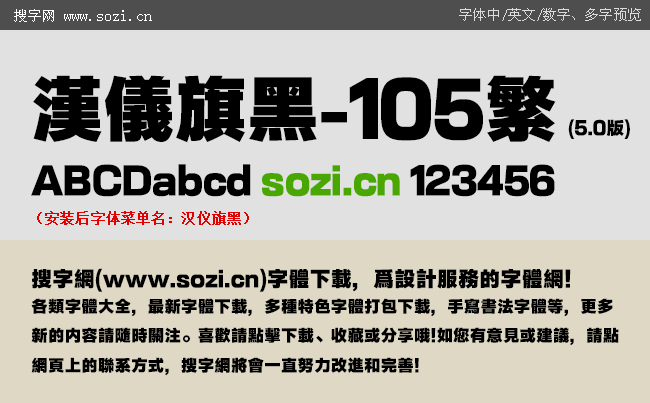
漢儀旗黑-105繁5.0版
漢儀旗黑-105繁5.0版是搜字網(wǎng)給大家提供一款漢儀字體公司出品的中文字體下載,旗黑以其勻稱的間架結(jié)構(gòu)、外擴(kuò)的中宮、克制的字面、干凈的筆形、定制的西文字符以及特殊的字重命名系統(tǒng),塑造了某種鮮明的第一印象。相信你一定會(huì)喜歡在自己作品中用到這款中文字體!歡迎下載!